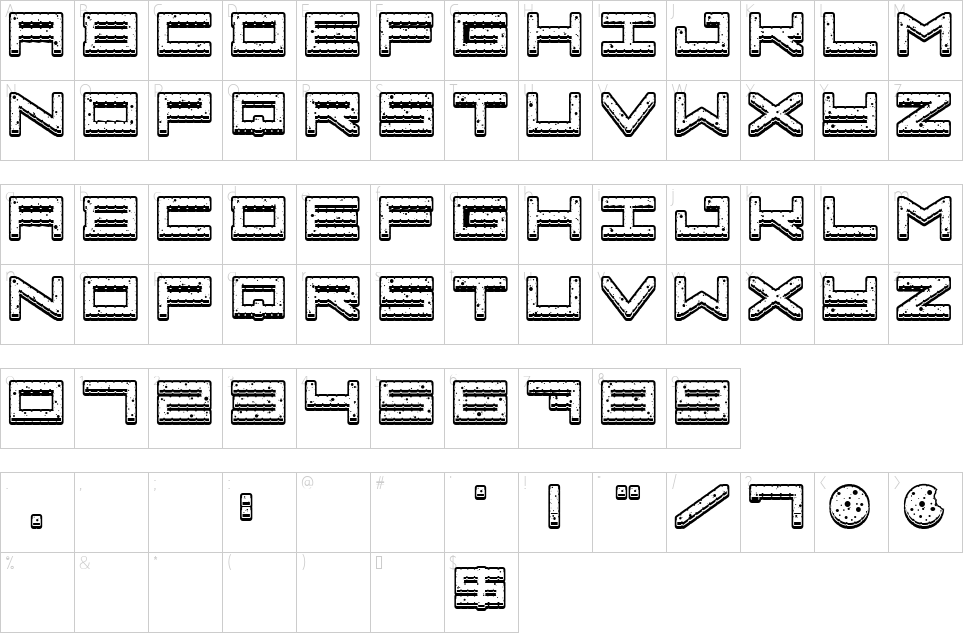
Descubra a fonte Crazy Cookies, um recurso grátis e divertido para seus projetos gráficos. Criada pelo designer Qkila, Crazy Cookies traz uma sensação descontraída e desconcertante que pode aprimorar seu design de maneira única. Esta fonte é uma excelente escolha para quem busca algo diferente e versátil. Ela foi baixada mais de 4.283 vezes, demonstrando sua popularidade entre os designers. Seja para criar rótulos atraentes, texturas originais ou qualquer outro projeto que você possa imaginar, Crazy Cookies é uma ótima opção. Descubra agora e adicione um toque divertido à sua próxima criação gráfica.